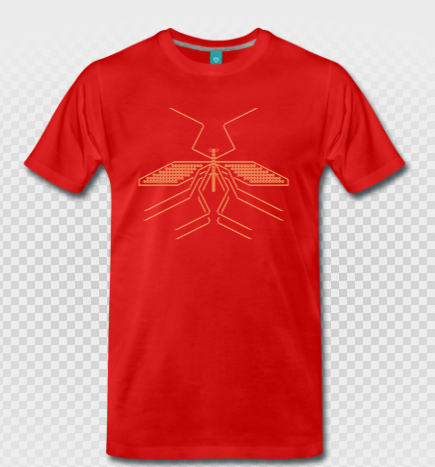
This is wonderful, Nature isn't just everywhere around us but also invading Fontstruct to make fonts natural -- I love it! 11/10
Congratulations! FontStruct Staff have deemed your FontStruction worthy of special mention. “insects” is now a Top Pick.
Love it!
pretty cool :D
Excellent creation - well done!
Wow...
Insekt
Dope!
Mensch super! YEEEET
Zuckersüß! Werde ich mir aufs T-Shirt drucken. :)
schick schick
like this!!!!!
Love it, wunderbare Idee :b
the ants just look so cute
Sehr schön
stabile arbeit bruder
is there a bee?
Diese Insekten sind das beste was ich jemals gesehen habe 😎
Das schönste was ich jemals gesehen habe!
Ich bin beeindruckte 🙂‍↕️🤣
Baba mäßig
Sehr sehr gut, mir gefällt die Libelle sehr gut...Insekten sind wahre Meisterwerke der Natur. Ihre filigranen Flügel, die oft in schillernden Farben glänzen, ihre komplexen Körperstrukturen und die Vielfalt ihrer Formen machen sie zu faszinierenden Lebewesen. Besonders die Symmetrie und die Details ihrer Muster – sei es bei Schmetterlingen, Käfern oder Libellen – zeigen eine unverkennbare Schönheit, die oft erst im Detail sichtbar wird. In ihrer Vielfalt und Anpassungsfähigkeit offenbart sich eine erstaunliche Ästhetik, die oft übersehen wird.
Krank!